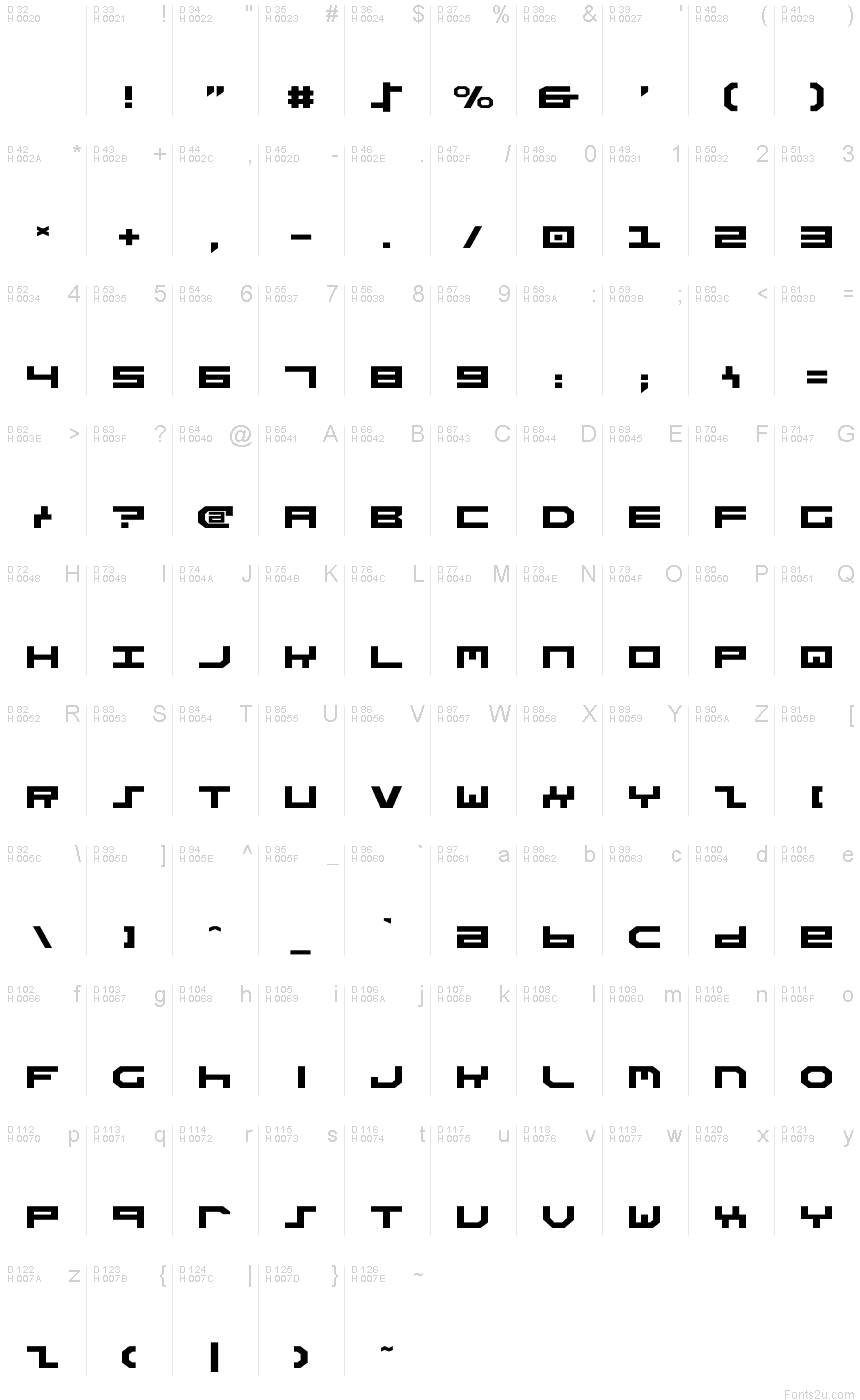
Stuntman Expanded من Iconian Font هو خط عرض مستقبلي مجاني، يحمل طابع القوة والأسلوب الصناعي لأفلام الخيال العلمي في أوائل الألفية. الحروف الكبيرة مصممة بزوايا مربعة وخطوط أفقية عريضة وقطع قطري دقيق، مما يمنح الخط طابعاً سريعاً وميكانيكياً ولمسة ريترو تشبه ألعاب الفيديو.
يعمل الخط بشكل طبيعي على الملصقات وشعارات الألعاب والعناوين وتصاميم الفعاليات التقنية وأغلفة القصص المصورة، حيث تحتاج الكلمات القصيرة إلى مظهر قوي ومحدد. وبكونه خطاً مجانياً، فهو مناسب أيضاً للشارات وأسماء الفرق والشعارات، حيث تضفي الحروف العريضة مظهراً مضغوطاً وشديداً حتى في النصوص المختصرة جداً.